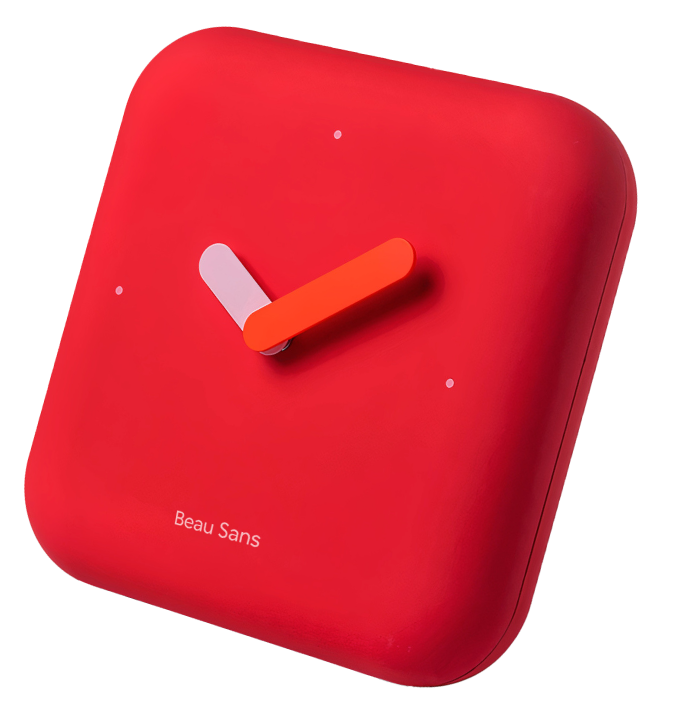
BT Beau Sans Typeface
BT BEAU SANS TYPEFACE
BỘ KÝ TỰ HỖ TRỢ NHIỀU
NGÔN NGỮ LATIN
Concept
triển khai
Chữ là thành phần tối quan trọng trong Branding, đóng vai trò then chốt trong hầu hết mọi điểm chạm có text. Với định hướng xây dựng cơ bản là geometric và humanist, concept triển khai Beau Sans lấy cảm hứng từ cuộc sống hàng ngày của chúng ta, khi con người và công nghệ ngày càng hòa nhập, nền tảng digital ăn sâu vào tiềm thức và trở thành một phần không thể thiếu của cuộc sống thường nhật.
Từ triết lý thiết kế kể trên, font chữ BT Beau Sans được triển khai với những chi tiết đặc thù kiến tạo nên sự khác biệt trong từng con chữ.
Tối ưu thị giác & trải nghiệm đọc
BT Beau Sans sở hữu thông số x-height lớn (tỉ lệ x-height/ascender xấp xỉ 70%) sẽ khiến các kí tự dễ dàng phân biệt với nhau. Tỉ lệ này đủ tốt để người dùng không bị nhầm lẫn “n” với “h” hay single-story “a” với “d”. Những đặc điểm kĩ thuật này đã góp phần làm tăng “legibility” cho BT Beau Sans theo đúng định hướng phát triển bộ chữ.
Beau Sans
is your next favourite
Sans Serif Typeface
Yếu tố
kỹ thuật
Thiết kế của Beau Sans là sự giao thoa giữa con người, công nghệ và kỹ thuật, được thể hiện qua hình thái kí tự cùng các yếu tố kỹ thuật chuyên biệt.